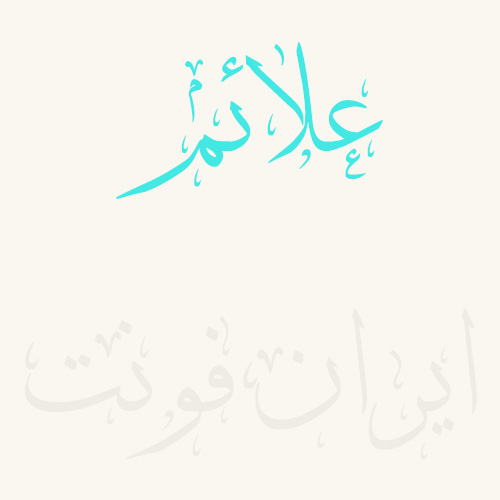
فونت ثلث نمایشی تزئینی با نام لاتین thuluth decorated همانند یک فونت ثلث واقعی و دانلود نسخه جدید فونت ثلث و فونت های خوشنویسی از سری فونت های ثلث تزئینی است که در ادامه مطلب بیشتر با این فونت نمایشی آشنا می شوید. خط ثلث (Thuluth): خط ثلث یکی از شیوه‌های بسیار مهم در خوشنویسی اسلامی و یکی از خطوط ششگانه است و ابداع آن را به ابوعلی بن مقله بیضاوی شیرازی (معروف به ابن مقله) که در قرن سوم هجری می‌زیست نسبت می‌دهند. خط ثلث با ساختاری ایستا و موقر، بیشتر در تزئین کتاب‌ها و کتیبه‌ها به‌کار رفته‌است. تکامل تدریجی ثلث به عنوان خطی تزئینی توسط ابن مقله، ابن‌بواب و یاقوت مستعصمی شکل گرفت. ابن‌بواب زیبایی و ظرافت را با خط ثلث همراه کرد. خط ثلث در ایران برای نوشتن عنوان سوره‌های قرآن کریم، پشت جلدنویسی، سرلوحه‌ها، و بخصوص در کتیبه‌ها و کاشی‌کاری‌ها به‌کار رفته‌است و هنوز نیز رایج است. خط رفیعی است که ارتفاع الف در آن هفت نقطه می‌باشد. بنابراین نسبت به خطوطی نظیر نسخ و نستعلیق و رقعه، بلندتر است. خطی است ایستا و ریتمی که در اثر تکرار، ضربه‌های عمودی و بلند حروف در این خط ایجاد می‌شود. القا کننده قدرت و عظمت است. این احساس خصوصاً در برخورد با کتیبه‌های زیبای ابنیه مذهبی روشن‌تر است. خط ثلث که در ایران مهم‌ترین کاربرد آن کتیبه نویسی است، دارای بار مذهبی نیرومندی است و برای نوشتن آیات قرآن استفاده می‌شود. فونت ثلث همچنین در مجله‌ها، پشت جلد کتاب‌ها، پوسترها، سرلوحه‌ها و طرح تمبر، بزرگداشت‌ها و… مورد استفاده قرار می‌گیرد. در کجا میتوان از فونت ثلث استفاده کرد ؟ در تمام پلت فرمها شامل تمامی نسخه های ویندوز، مک، ios، اندروید، وب و… قابل استفاده است.